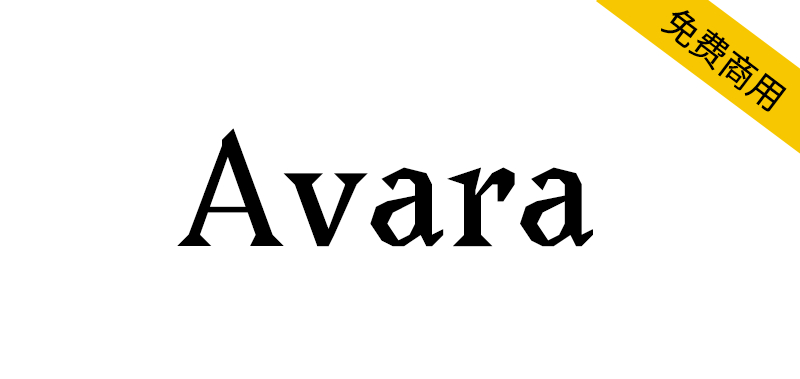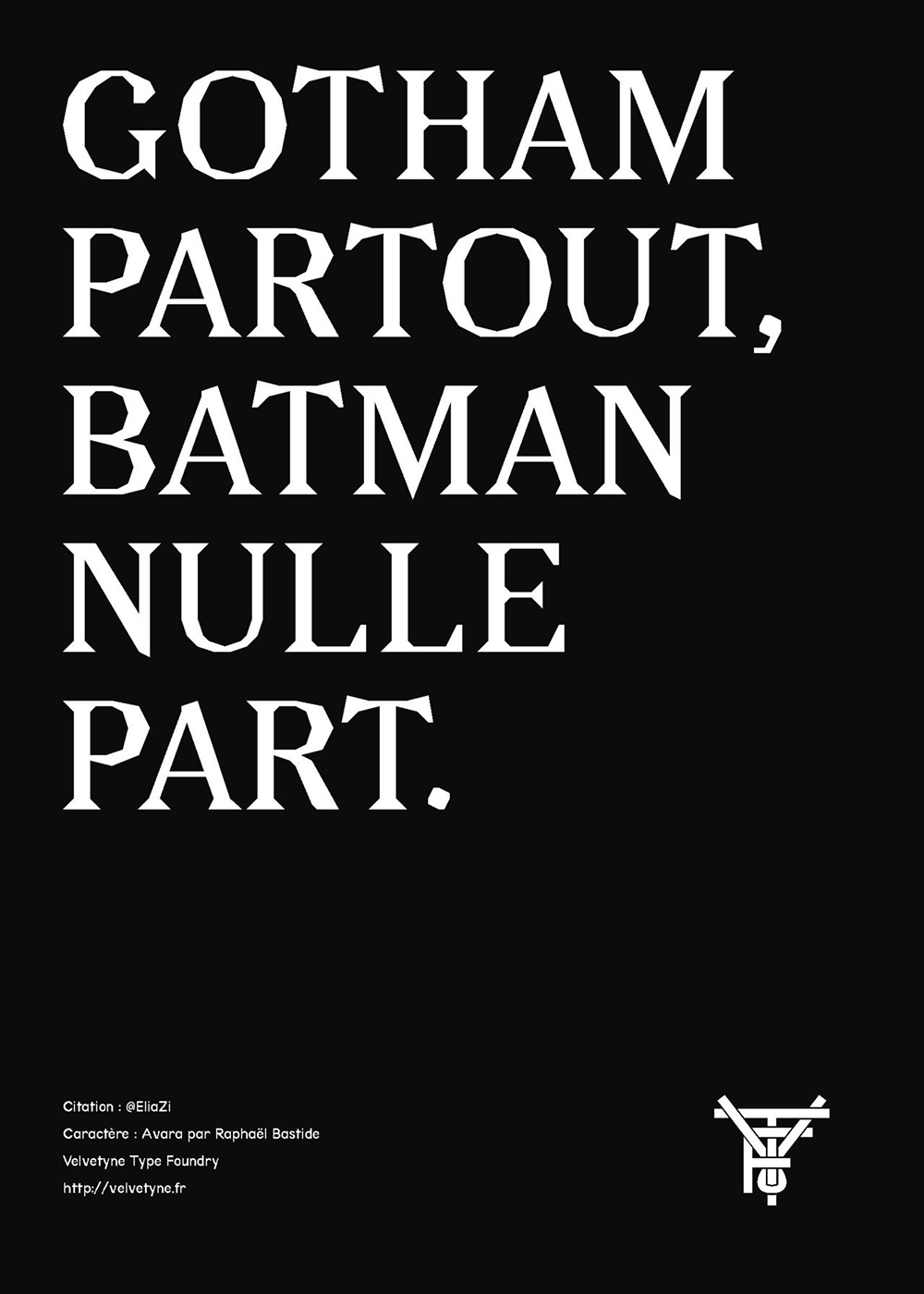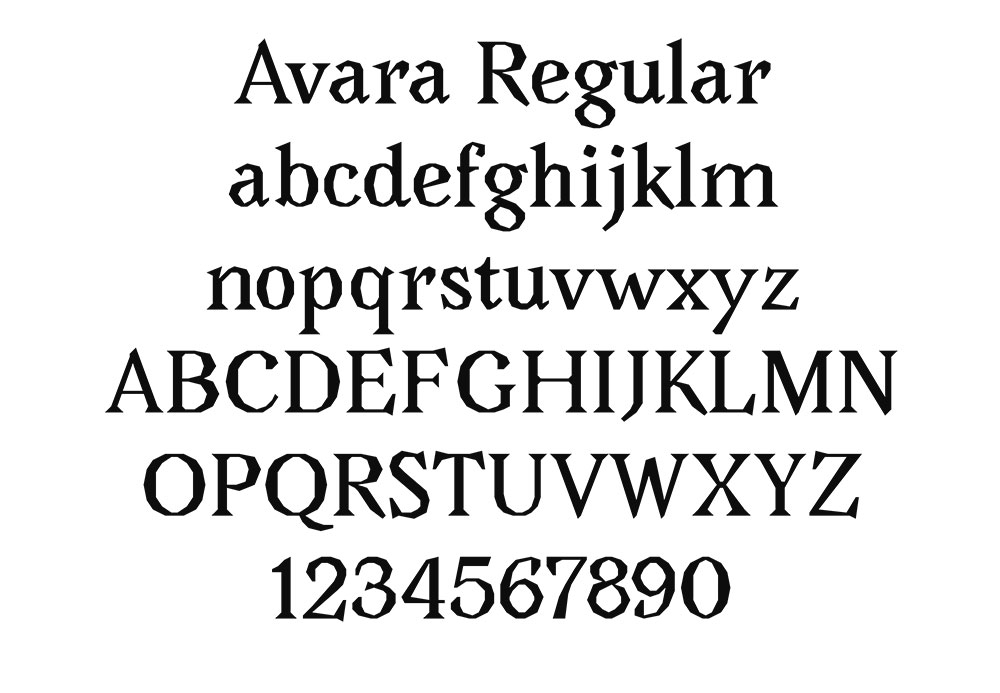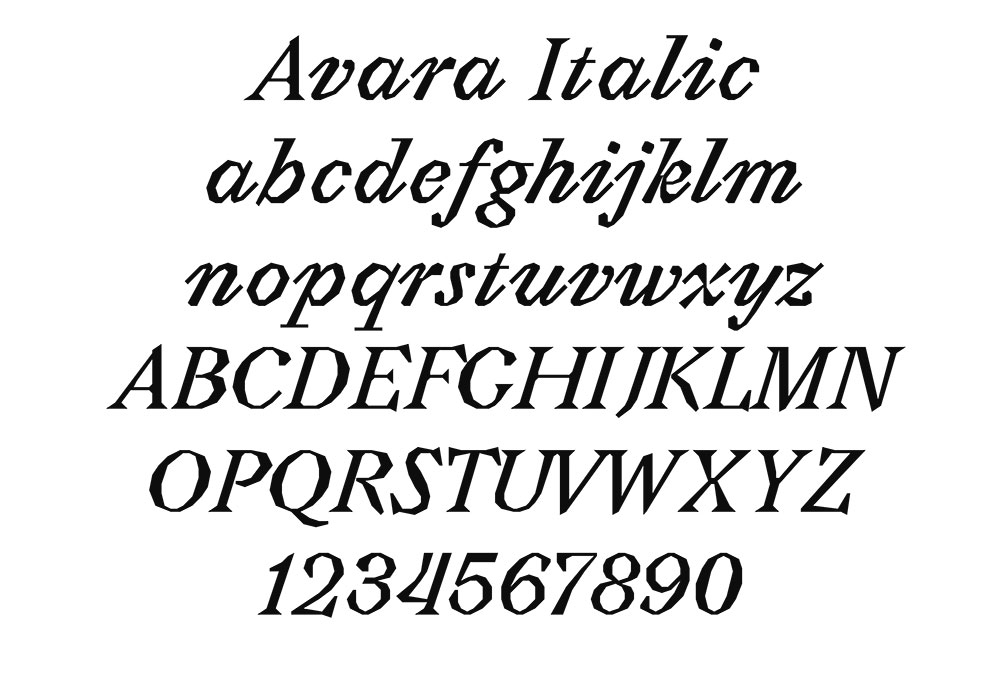
Avara是一个自由的过渡衬线无曲线字体系列。其节点的位置完全基于粗糙的方形网格。这种设计选择的最初原因是为了促进字体上的协作,现在它导致了这个字体系列的激进和高度约束的形状。它于2011年11月由Raphaël Bastide启动并首次发布。
Avara is a libre transitional serif curveless type family. The placement of its nodes is exclusively based on a rough square grid. The original reason of this design choice was to facilitate collaboration on the font, and it now results in the radical and highly constrained shapes of this type family.